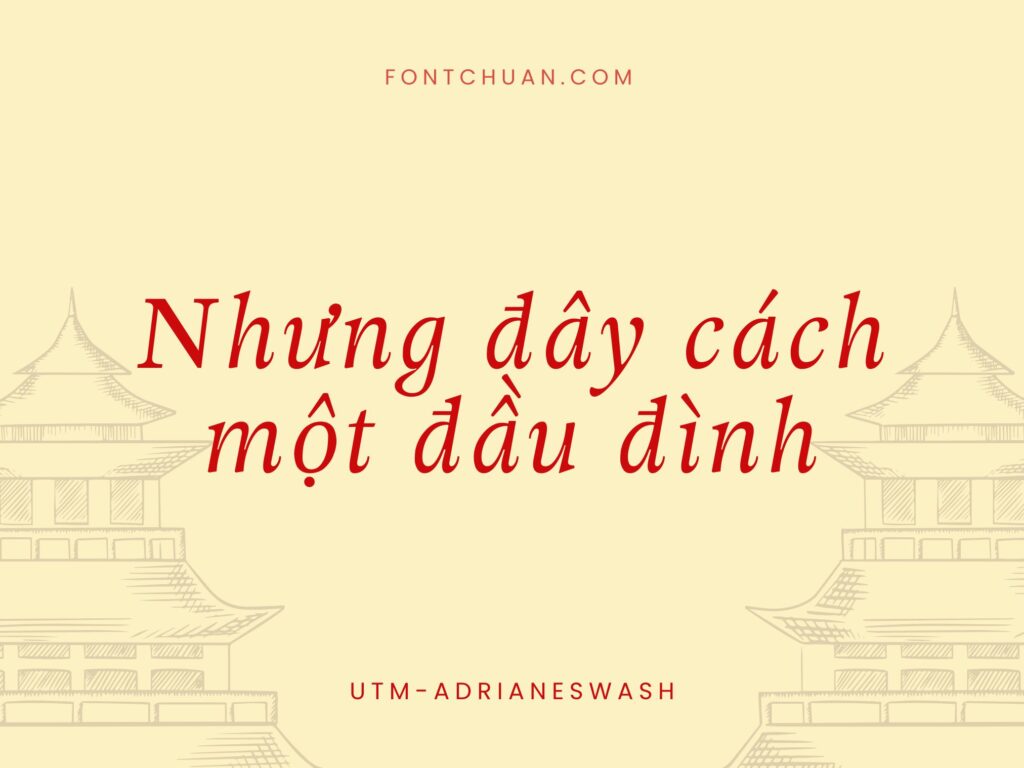
Font UTM Adriane Swash Việt Hóa
Adriane Swash là một Font Serif cao cấp được thiết kế bởi Marconi Lima và phát hành bởi Typefolio Digital Foundry. Font mang phong cách cổ điển kết hợp với yếu tố hiện đại, đặc biệt với những ký tự swash được thiết kế uyển chuyển và mềm mại. Phiên bản Việt hóa được thực hiện bởi Đinh Kiên, cho phép hỗ trợ đầy đủ tiếng Việt cùng hơn 100 ngôn ngữ khác. Font đã được thành viên của Font Chuẩn sưu tầm và chọn lọc kỹ lưỡng để đáp ứng nhu cầu sử dụng trong các thiết kế đòi hỏi tính nghệ thuật và trang trọng cao. Ngoài ra, Adriane Swash cũng có thể được xem như một Font chữ bất động sản nhờ vào phong cách sang trọng, dễ gây ấn tượng trong các ấn phẩm giới thiệu dự án, hồ sơ năng lực hay tài liệu quảng bá lĩnh vực này.
Adriane Swash có cấu trúc chữ thanh mảnh, chân chữ nhẹ nhàng cùng với độ tương phản cao giữa nét thanh và nét đậm, mang lại vẻ đẹp quyến rũ và dễ nhận diện. Với hệ thống ký tự mở rộng cùng các swash đi kèm, font trở nên lý tưởng cho các ứng dụng như tiêu đề, thiệp cưới, thiết kế logo, bao bì sản phẩm và ấn phẩm in ấn trang trọng. Những ngành nghề như quảng cáo, bất động sản, spa và giáo dục có thể tận dụng Adriane Swash để tạo điểm nhấn sang trọng và chuyên nghiệp trong thiết kế.